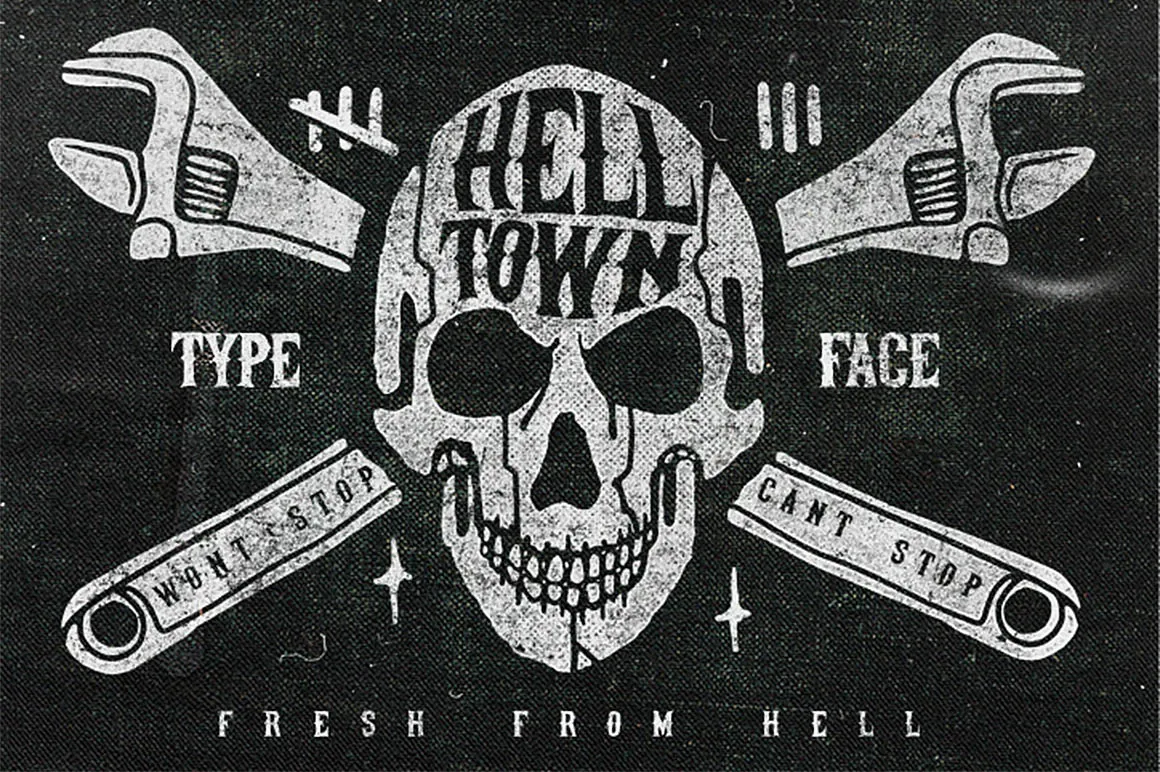
Helltown Font – Fonte Grátis
Helltown Font
A fonte Helltown Font é uma criação minimalista mas muito interessante do designer Hamilton. Com seu estilo vintage peculiar e feito à mão usando a técnica de desenho, ela se destacaria perfeitamente para trabalhos decorativos modernos e vintage. Ideal tanto para artistas digitais quanto para designers gráficos que buscam um recurso único, essa fonte oferece uma combinação única entre elegância e personalidade, dando seu projeto aquele toque especial e original. Seja você um criador de arte digital querendo dar vida à sua obra ou um designer gráfico buscando adicionar algo diferente a seus projetos, Helltown Font é certamente o recurso perfeito para aprimorar qualquer design. Instale-a agora e descubra como ela pode transformar seu trabalho em algo realmente único e inovador.